Việc ghép cặp font chữ phù hợp có thể làm cho thiết kế của bạn có điểm nhấn tạo sự hài hoà và thu sự chú ý của người dùng, ngược lại nó cũng khiến cho thiết kế của bạn trông rất hỗn độn và gây khó chịu cho người xem. Chúng ta thường có 3 cách ghép chữ chính là:
1. Sử dụng font chữ cùng một family
Cách dễ nhất để tìm cặp font chữ hoàn hảo là sử dụng các font chữ khác nhau trong cùng một nhóm font chữ bao quát. Nó thường gọi là ‘superfamily’ và bạn sẽ có một loạt các chữ số, kiểu dáng và type face được thiết kế riêng để làm việc cùng nhau.
Superfamily chẳng hạn như serif và một phiên bản sans-serif của cùng một kiểu chữ: các ví dụ nổi tiếng bao gồm Lucida/Lucida Sans và Meta/Meta Sans.
2. Ghép cặp kiểu chữ tương phản
Ngược lại, như tên gọi của nó, là về ghép các cặp chữ hoàn toàn khác nhau – nhưng nó vẫn bổ sung kiểu chữ phù hợp với từng ứng dụng dự định của chúng.
Thông thường các bạn có thể tăng độ tương phản giữa hai font bằng cách chọn một font đậm và tối (dark and heavy) sẵn trong khi font kia dạng bình thường. Khi áp dụng lên văn bản, font đậm sẽ được dùng cho phần tiêu đề và font bình thường cho phần nội dung cụ thể, đó là một cách thực hành tốt hơn cả.
3. Xung đột
Một quy tắc khác nên nhớ là không nên chọn các font quá giống nhau. Đứng ở góc độ người đọc tất nhiên bạn sẽ không muốn ai bắt bạn phải căng mắt ra để phân biệt sự khác nhau giữa hai loại font phải không? Việc đó sẽ phá vỡ tính rõ ràng và hạn chế người đọc tiếp cận nội dung trình bày do người đọc không thể lướt nhanh và nắm được tổng quan nội dung của toàn bộ thiết kế được.
Khi bạn muốn có sự nổi bật trong thiết kế thì cần phải tránh tạo ra sự xung đột khi kết hợp những font chữ. Dưới đây là cách để tránh các xung đột:
- Hãy chú ý đến danh mục của font chữ: thật thú vị khi sử dụng serif hoặc script cùng nhau, nhưng đó là một cách kết hợp khá khó khăn. Đảm bảo rằng các font chữ bạn chọn hợp nhau để tránh xung đột.
- Duy trì cấu trúc phân cấp: lưu ý sử dụng kích thước và độ dày để giúp phân biệt giữa các font chữ. Phân cấp là chìa khóa, vì vậy hãy chắc chắn rằng bạn lựa chọn đúng các font chữ có thể làm nổi bật tầm quan trọng tương đối của các phần khác nhau của văn bản trong thiết kế của bạn.
- Sử dụng màu sắc: hãy sử dụng màu sắc cho lợi thế của bạn để giúp phân biệt các phân đoạn văn bản và tạo phân cấp.
Từ những nguyên tắc trên, chúng tôi đã tổng hợp được 32 cách ghép nối font chữ mà chắc chắn sẽ khiến bạn hài lòng.
1. Calvert và Acumin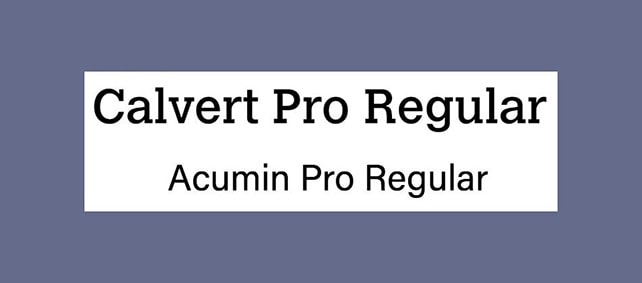
2. Montserrat và Courier New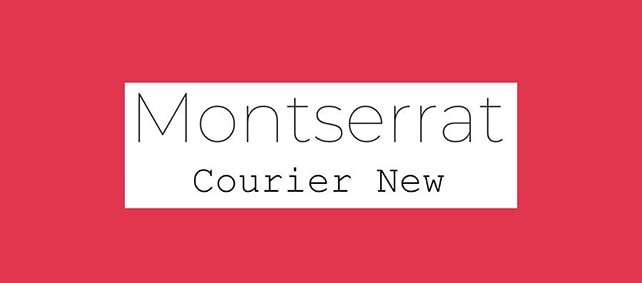
3. Skolar Latin và Proxima Nova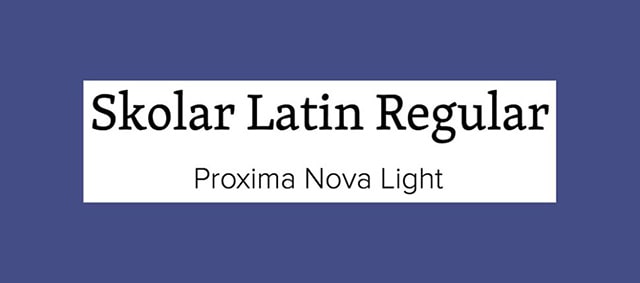
4. Alegreya Sans SC và Source Sans Pro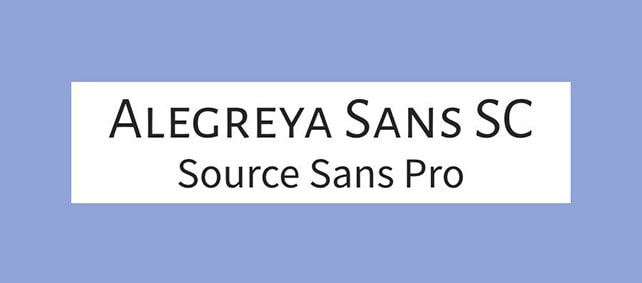
5. Pacifico và Quicksand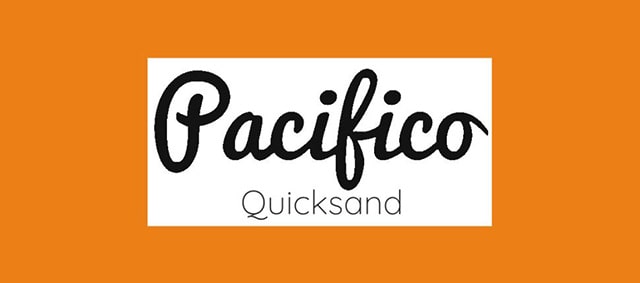
6. Julius Sans One và Archive Narrow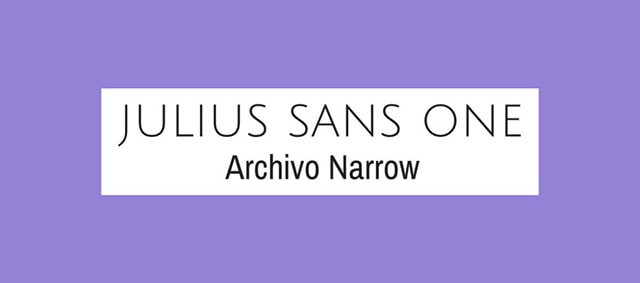
7. Playfair Display and Raleway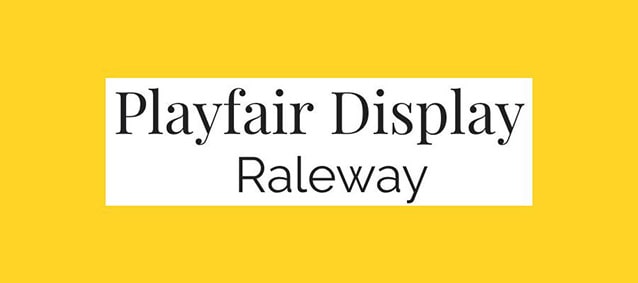
8. Oswald và Lato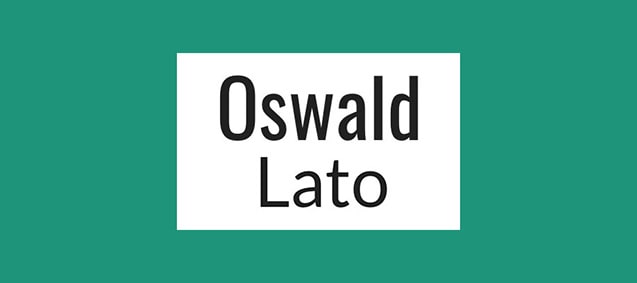
9. Super Grotesk và Minion Pro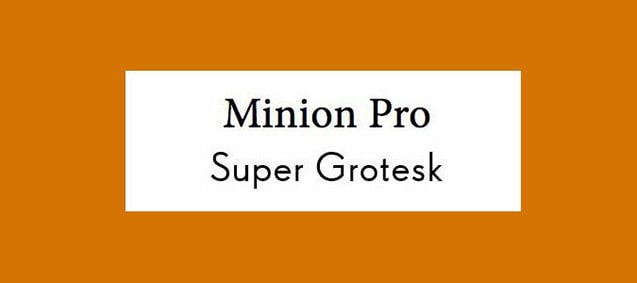
10. Libre Franklin và Libre Baskerville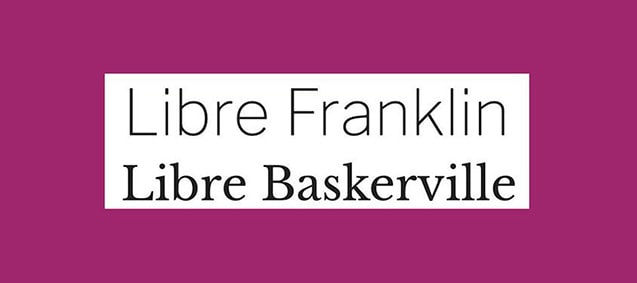